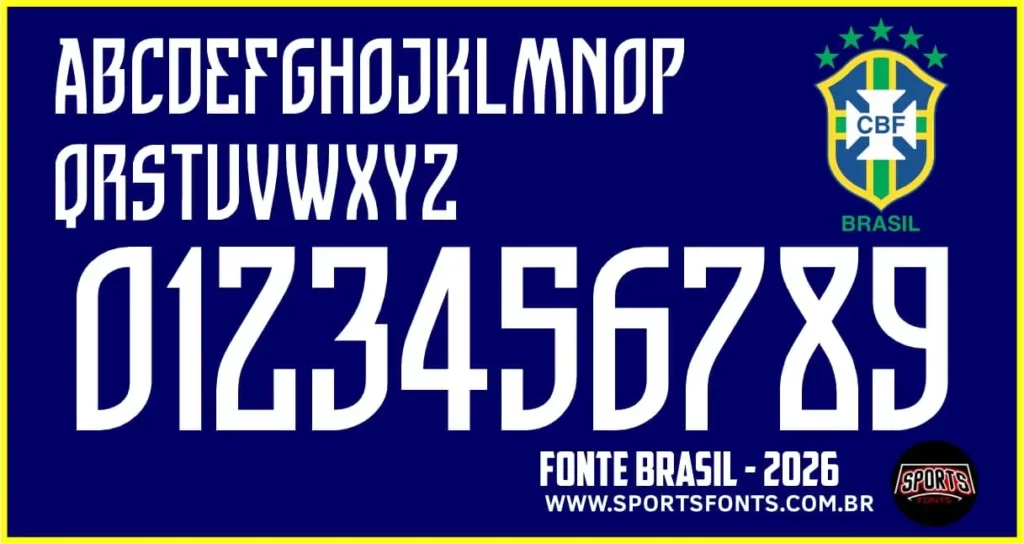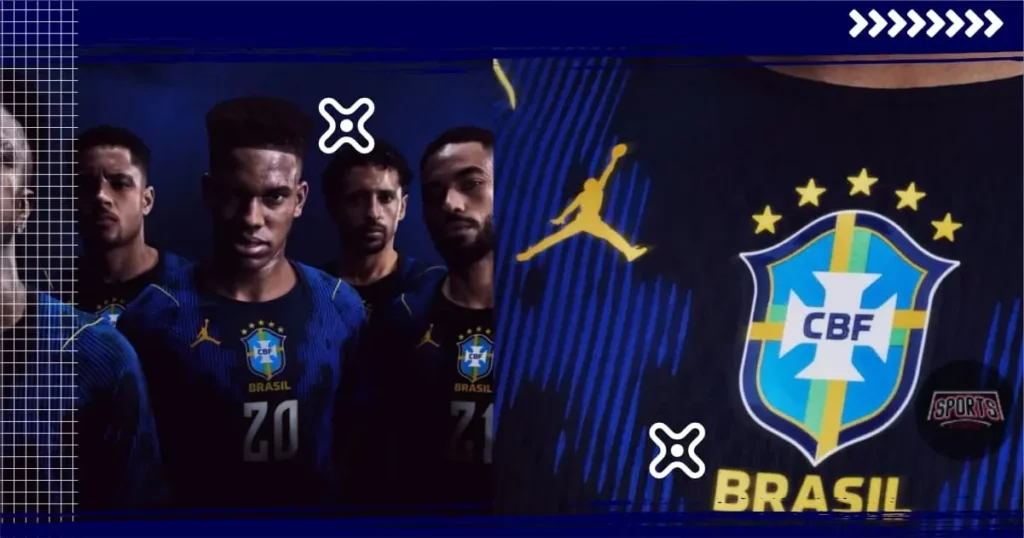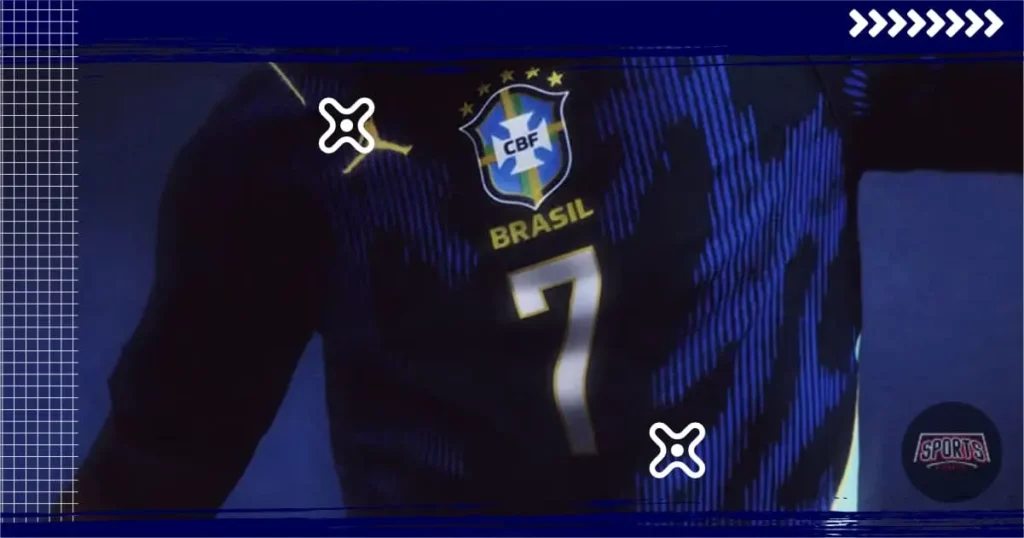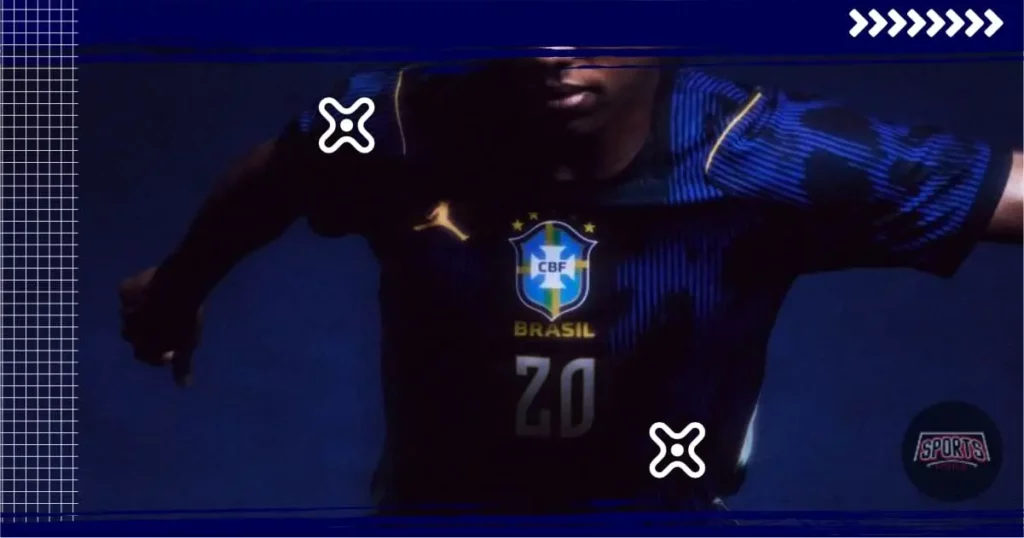
A Seleção Brasileira entra em uma nova era em 2026, e não estamos falando apenas de tática. Pela primeira vez na história, o icônico “Jumpman” da Jordan Brand estampa o manto reserva azul, trazendo uma fusão inédita entre a cultura do basquete e a tradição do futebol pentacampeão. Mas para nós, o grande destaque vai além do escudo: a nova Fonte Seleção Brasileira 2026 (tipografia) desenvolvida para a Copa do Mundo é uma verdadeira aula de design agressivo e moderno.
O Design da Fonte Seleção Brasileira 2026:
Diferente das curvas suaves vistas em 2024, a fonte de 2026 aposta em cortes angulares e formas geométricas rígidas. Sob o lema “Joga Sinistro”, o design busca refletir o instinto predatório da fauna brasileira. Os números apresentam um detalhe interno vazado que cria uma sensação de profundidade, ideal para quem busca um visual futurista e de alta performance.
Nossa Versão (By Sports Fonts):
Como de costume, aqui na Sports Fonts, realizamos o processo de vetorização detalhada para entregar uma versão fiel e de alta qualidade dessa tipografia. Nosso objetivo é fornecer um material de referência para designers que trabalham com mockups, artes esportivas e personalização de conceitos, sempre prezando pela precisão das formas e espaçamentos originais.
- Elementos: Alfabeto Completo e Numeração
- Destaque: Detalhes internos preservados para aplicação em qualquer cor.